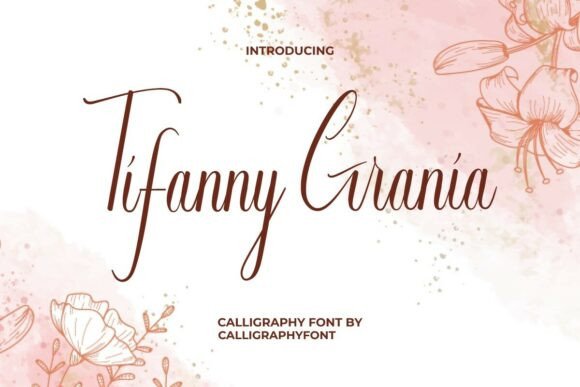
Tifanny Grania
Nếu bạn đang tìm kiếm các tài nguyên chất lượng cao như Tifanny Grania, gói cao cấp này là một lựa chọn tuyệt vời cho các dự án sáng tạo của bạn.
Cho dù bạn đang tạo sản phẩm POD (In theo yêu cầu), thiệp mời đám cưới hay đồ họa mạng xã hội, Tifanny Grania đều là một sự lựa chọn lý tưởng.